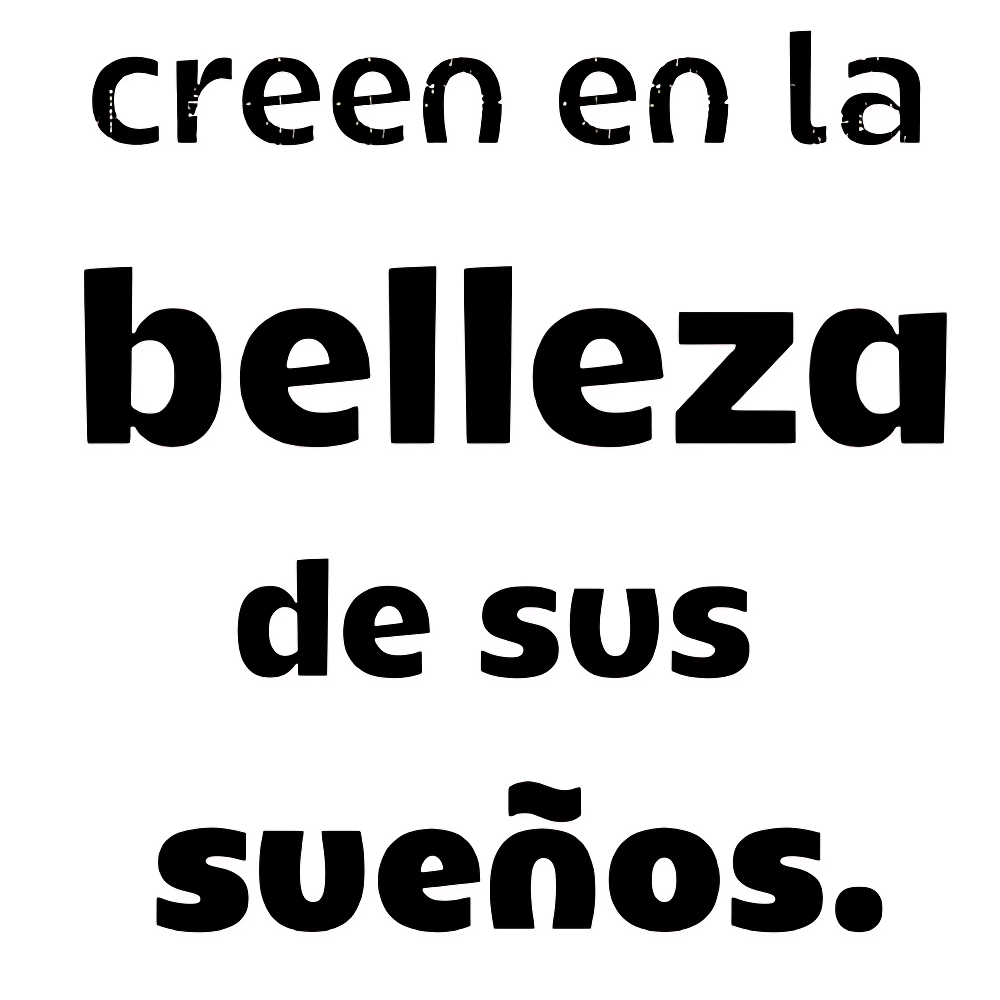
Kiara Rounded
| Descripción | Kiara Rounded es una variante de "Kiara" que contiene en esta familia el alfabeto cirílico en todos sus pesos además de tener alternativas y la versión "Rough", una familia muy completa especialmente para títulos. |